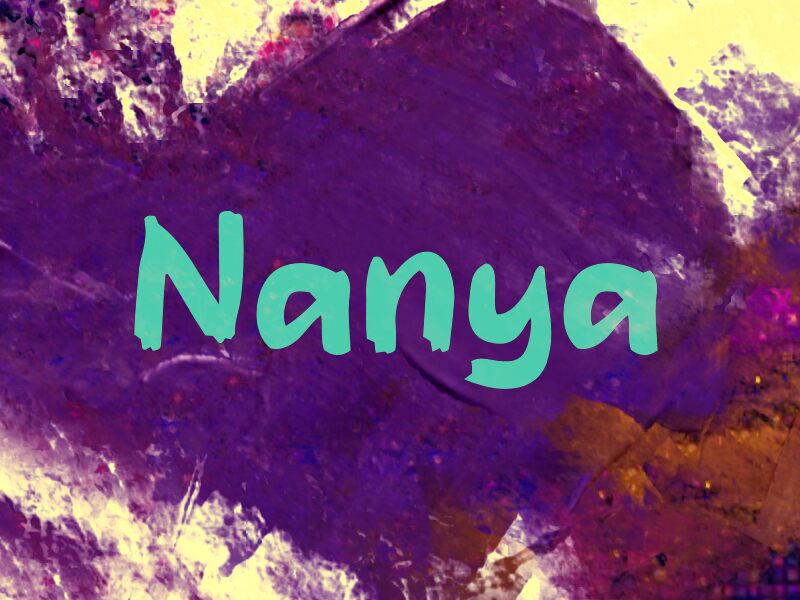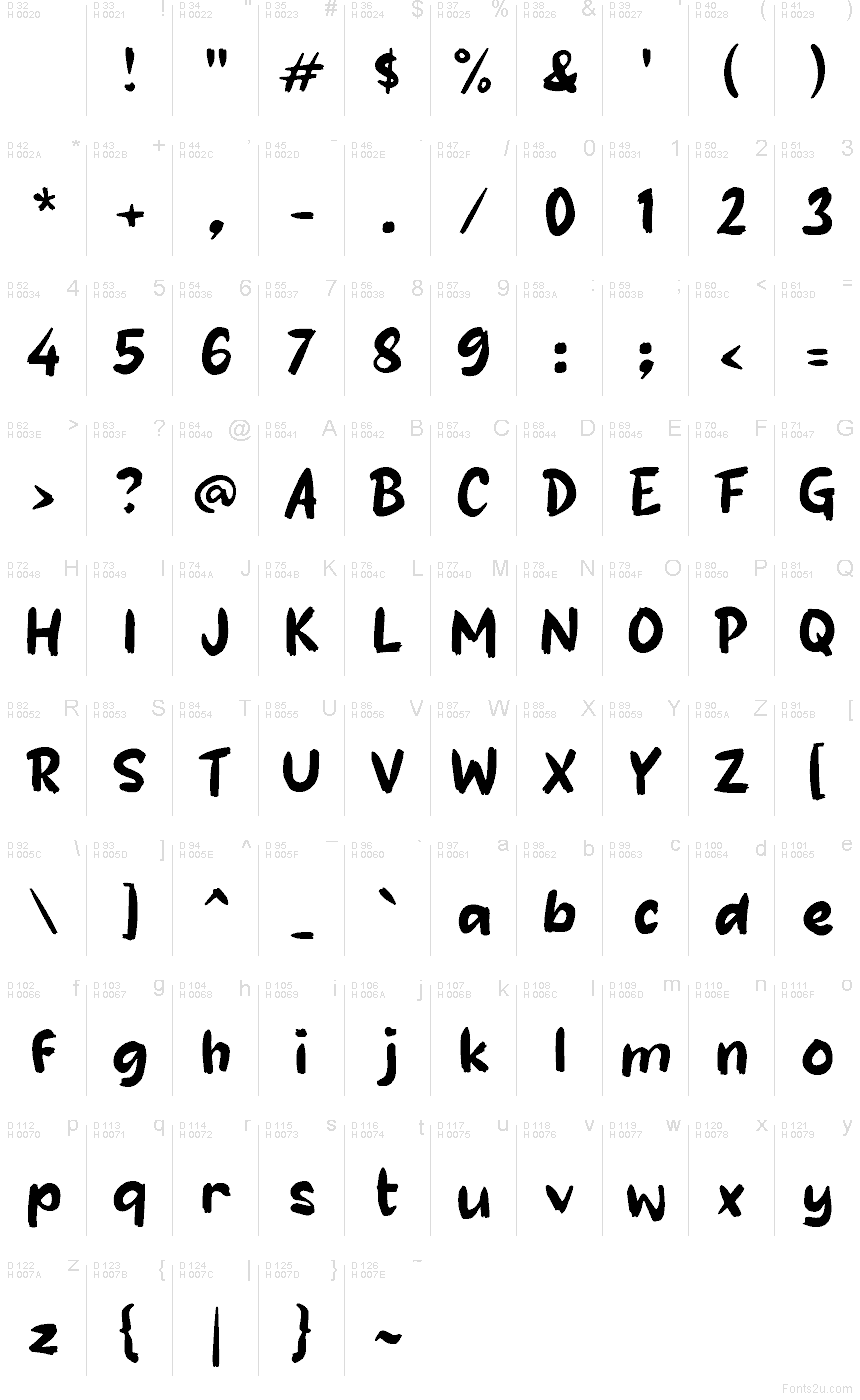
Nanya par Wep est une police de style pinceau gratuite, au rendu décontracté et peint à la main. Ses lettres paraissent larges, douces et légèrement irrégulières. Avec ses terminaisons franches et son rythme souple, l’ensemble du design dégage une impression de spontanéité, de convivialité et une touche de fraîcheur.
Elle s'intègre naturellement dans les titres d'affiches, l'identité visuelle de cafés, les étiquettes de produits, les visuels pour réseaux sociaux et les textes courts où une touche humaine, faite main, est nécessaire sans être trop complexe. Grâce à ses formes arrondies et bien pleines, Nanya convient également aux cartons de titres et aux mots-logos courts qui appellent un esprit décontracté et artistique.
Nanya
Présentation et spécimen de la police Nanya